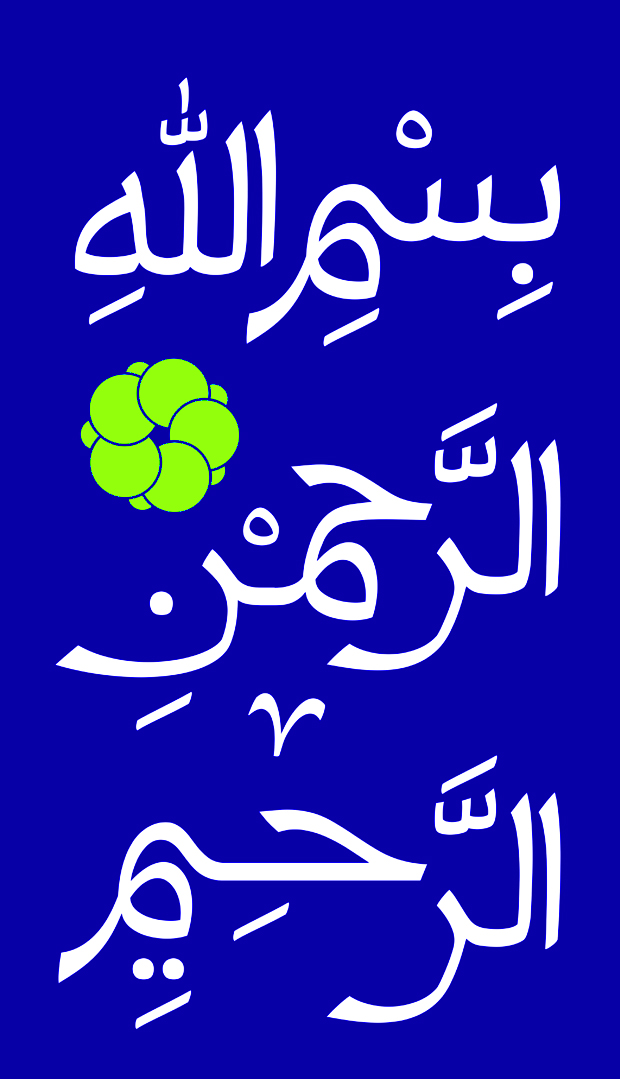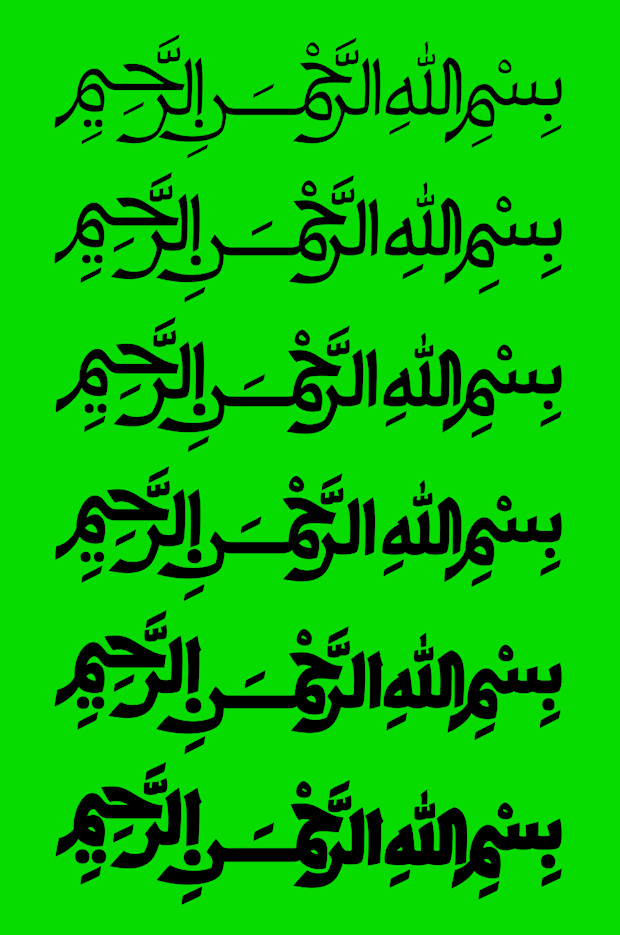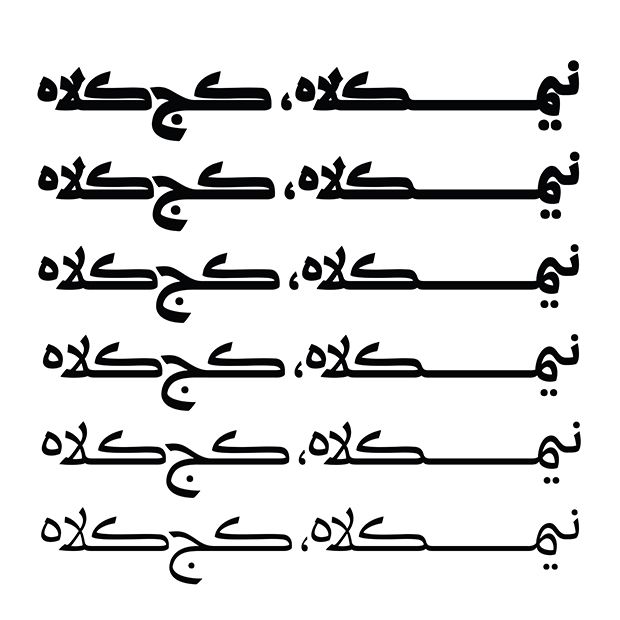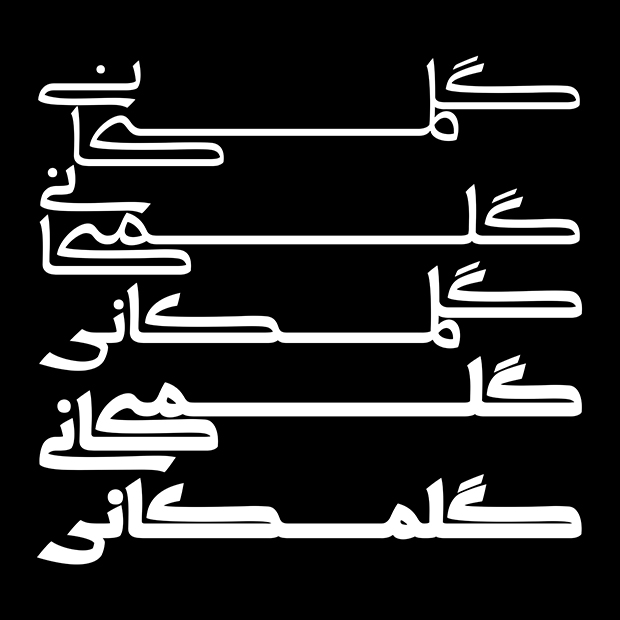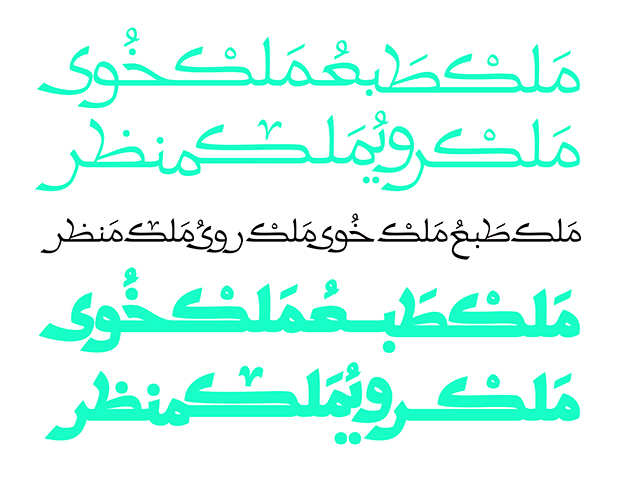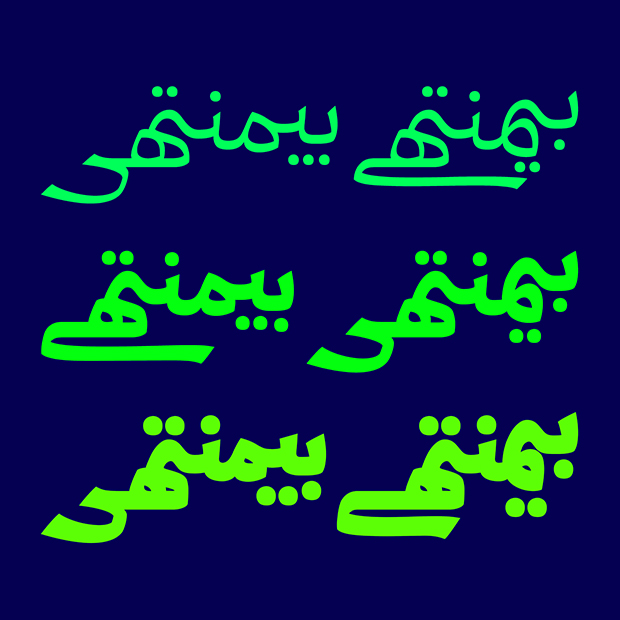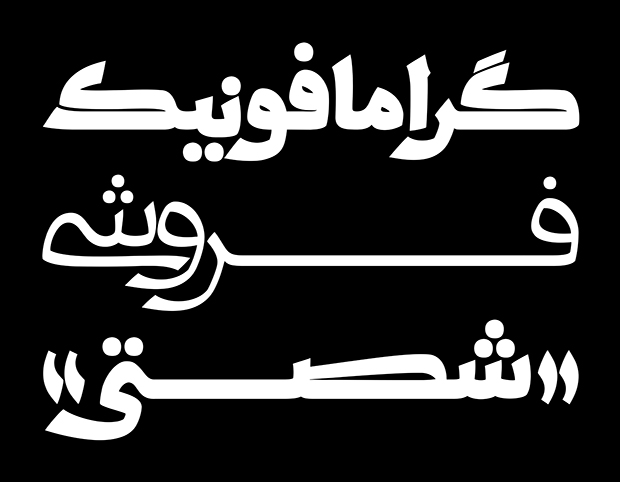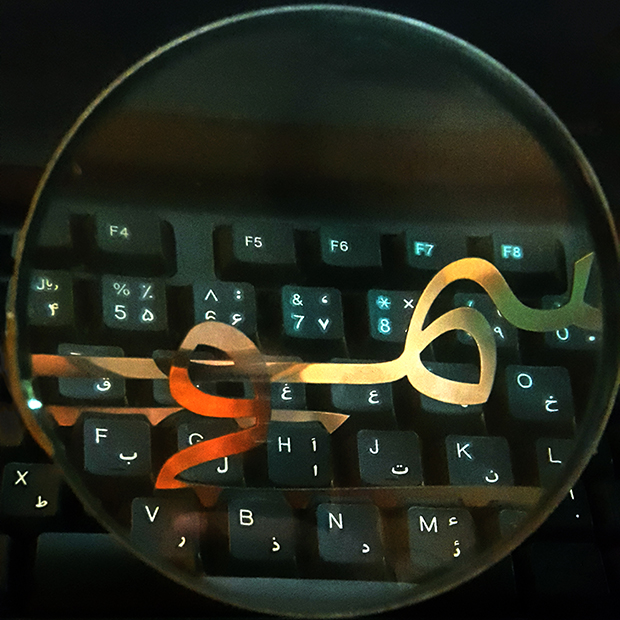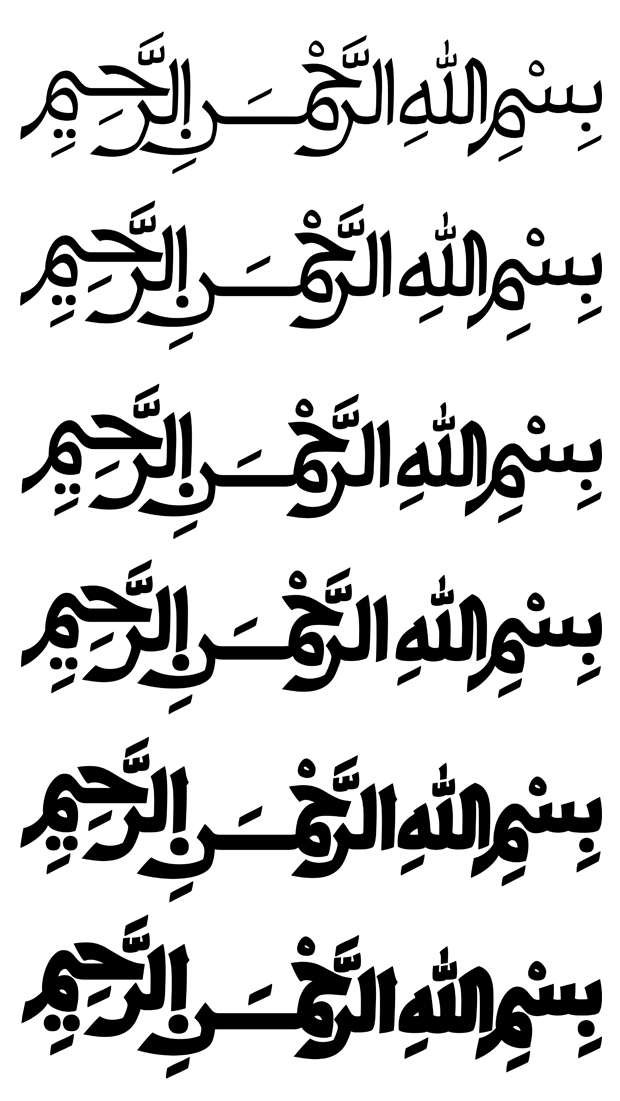
درباره قلم ایلیا
با تسلط اعراب بر ایران، خط کوفی که یکی از خطهای اصلی آنان در دوره آغازین اسلامی بود، در ایران رواج یافت. * این خط و نمونههای منشعب شده از آن تا سده چهارم هجری مورد توجه بود. با رواج خط نسخ اولیه به دلیل سرعت در نگارش، خط کوفی وارد مرحله دیگری شد و جنبه تزیینی به خود گرفت. این خط دارای انرژیهای بصری متفاوتی نسبت به دیگر خطوط نظیر نسخ، ثلث و... پس از خود داشت و این نکته مورد توجه و اهمیت قرار گرفت. با توجه به نتایج بدست آمده از پژوهش و بررسیهای انجام شده بر روی خطوط کوفی مختلف مانند کوفی مغربی، شرقی، گرهدار و... به جای مانده از سدههای نخستین هجری، دیزاین یک تایپفیس جدید از منظر فرم اما متکی بر چند ویژگی خاص و مطرح خطوط کوفی، هدف اصلی طراحی تایپفیس ایلیا بود..
نکته حائز اهمیت در دیزاین این تایپفیس باز آفرینی خط کوفی نبوده است، بلکه توجه و استفاده از ظرفیتهای بصری خطوط سنتی و سابقهدار برای تایپ و فرهنگ دیداری امروزی با نگاه متفاوتتری است تا بتوان با رویکردی جدید و مدرن به آن پرداخت. در طراحی تایپفیس ایلیا از ساختار خطهای نسخ و ثلث و در مواردی از خط تعلیق نیز استفاده شده است. از ویژگیهای دیگر این تایپ وجود اتصالات مختلفی است تا طراح گرافیک و تایپوگرافر بتواند ترکیبات مختلفی را تجربه و طراحی کند.
این پروژه در اواسط تابستان ۱۳۹۳ روند پژوهشیاش شروع و در اواخر زمستان همان سال وارد مرحله طراحی شد و در اواسط پاییز ۱۳۹۵ طراحی آن در ۴ وزن به پایان رسید. با توجه به تصمیم انتشار آن و همچنین امکانات تایپوگرافی نرمافزار قلم برتر شرکت نرمافزاری مریم با شروع سال ۹۹ مجددا بازنگری بر روی آن صورت گرفت و دو وزن دیگر نیز به آن اضافه شد.
* حمیدرضا قلیچخانی، درآمدی بر خوشنویسی ایرانی، نشر فرهنگ معاصر